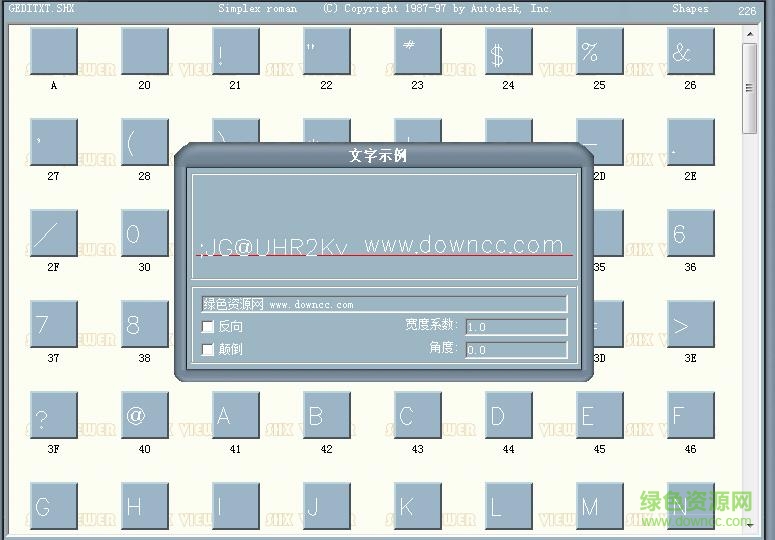
geditxt.shx字體的字體樣式不局限與漢字還能夠?qū)⒈姸嘧址麛?shù)字符號,鋼筋符號實現(xiàn)字體輸入的效果,讓你輕松的打出眾多字體符號,在制作的時候提升了制作cad制圖速度!
這款字體的使用效果在于能夠完美的定制出工程師們所需的字符樣式,在調(diào)用的過程中完美的實現(xiàn)你所需的各項制圖效果!
1、為了滿足用戶們?nèi)找嬖鲩L的各行各業(yè)的制圖字體需求,.shx字體文件正以最快的速度不斷制作而出滿足用戶需求
2、這款字體調(diào)整縮小了字體的高度,使之與流行的漢字字體體型相匹配